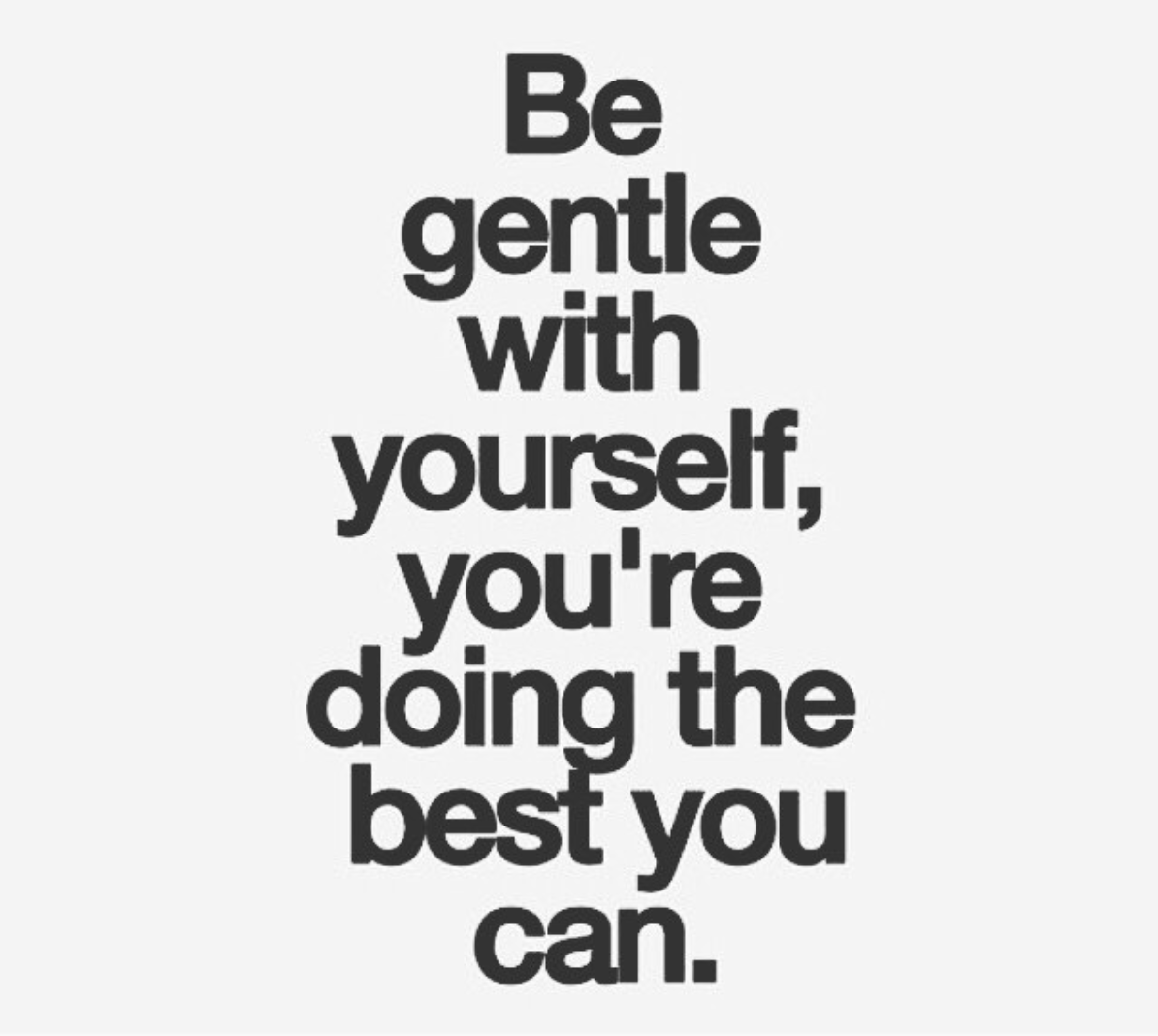
Suche Schrift von Instagram-Posting
vielleicht könnt Ihr mir helfen den Font aus diesem Instagram-Post zu identifizieren:
Weitere Beispiele habe ich leider nicht finden können.
Das sieht mir nach einer „Helvetica Neue bold“ aus. Allerdings scheint mir, dass da jemand noch eine schwarze Outline drum gelegt hat und es könnte auch sein, dass die Schrift in der Breite einen Hauch gestaucht wurde. Außerdem wurde die ursprüngliche Laufweite verringert. Das ist sehr typisch für diese Sinnspruch-Plakate, die seit ein paar Jahren außerordentlich beliebt sind. :-D
Und die Botschaft passt  auch noch sooooo perfekt auf den Gestalter dieser … ähm … sagen wir mal … »Arbeit«.
Mir geht es ausschließlich um die verwendete Schrift.
An die Helvetica musste ich auch als erstes denken, allerdings sind einige Buchstaben, insbesondere  der Buchstabe “a” im Schriftschnitt “Bold” anders.
Ja. Ab der Strichstärke Bold hat die Helvetica diesen Abstrich am a nicht mehr. Aber wie Kathrin schon sagt: eine Outline drumrum (z.B. vom Medium-Schnitt der Neuen Helvetica) und das gewünschte Ergebnis entsteht.
Das s sieht auch ziemlich verhunzt aus.
Ehrlich gesagt würde ich lieber eine Alternative nutzen, bei der man ohne semiprofessionelle Basteleien zu einem optimaleren Ergebnis kommt. Zum Beispiel die Neue Haas Grotesk (Display) und für das Schwänzchen-a die Alternativ-Sets nutzen (siehe Zeile 3):
Aber irgendwie muss man  doch das "you're doing the best you can" unterstreichen … :party: Nicht dass am Ende noch ein richtiger Apostroph verwendet wird ;-)